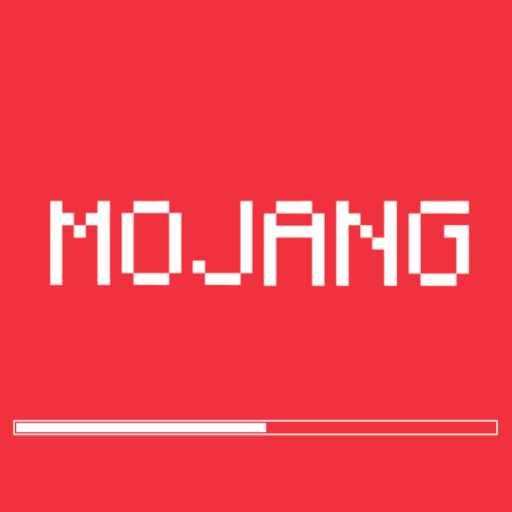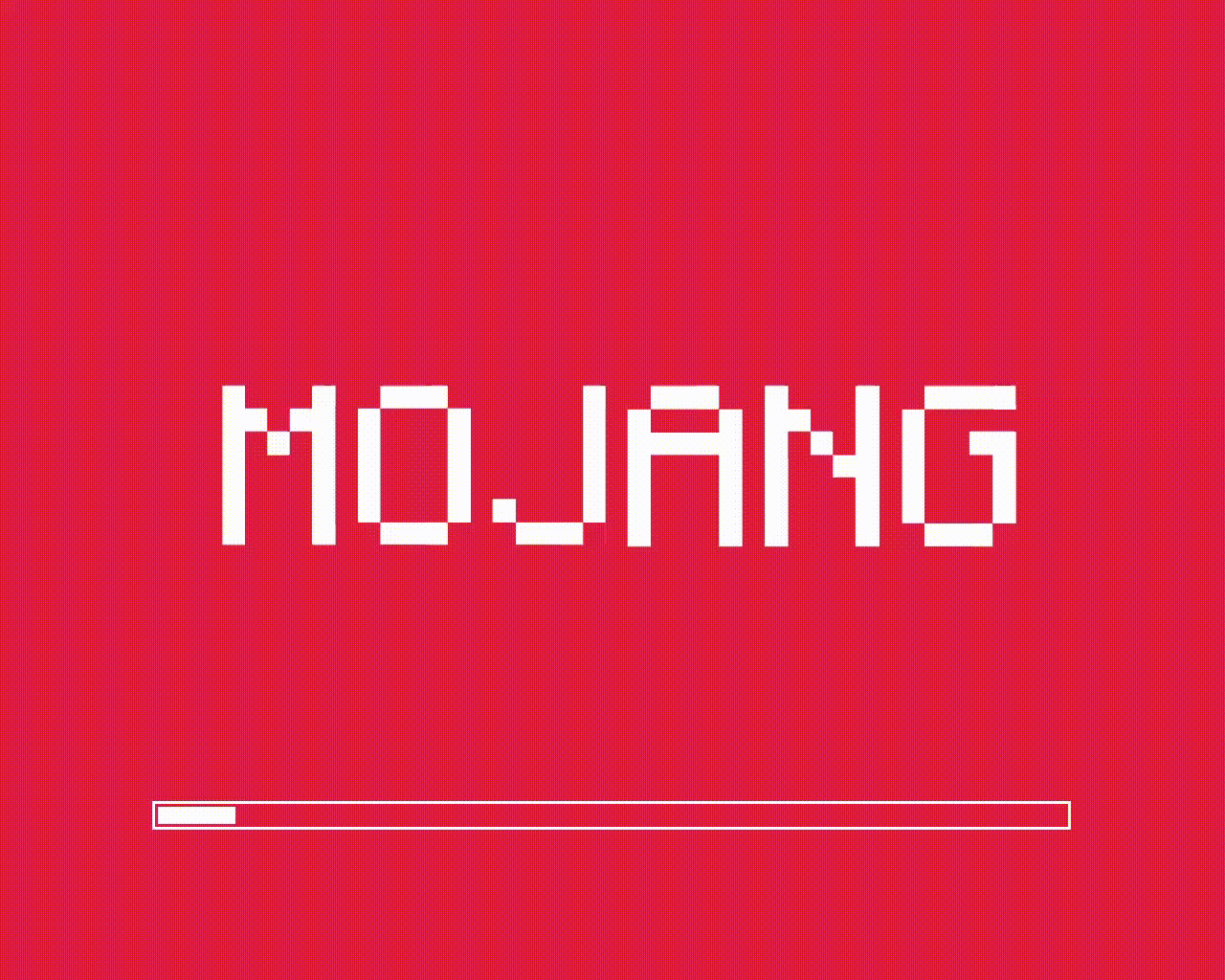
Minecraft font Mojang logo (Only Optifine)
Этот ресурспак предлагает стильное преображение начального экрана загрузки игры. Вместо стандартного шрифта и классического вида логотипа Mojang используется оригинальный шрифт Minecraft, что создаёт более гармоничное и тематически выдержанное визуальное оформление.
Подходит для игроков, которые хотят придать своему Minecraft более целостный и стилистически завершённый вид уже с момента запуска игры.